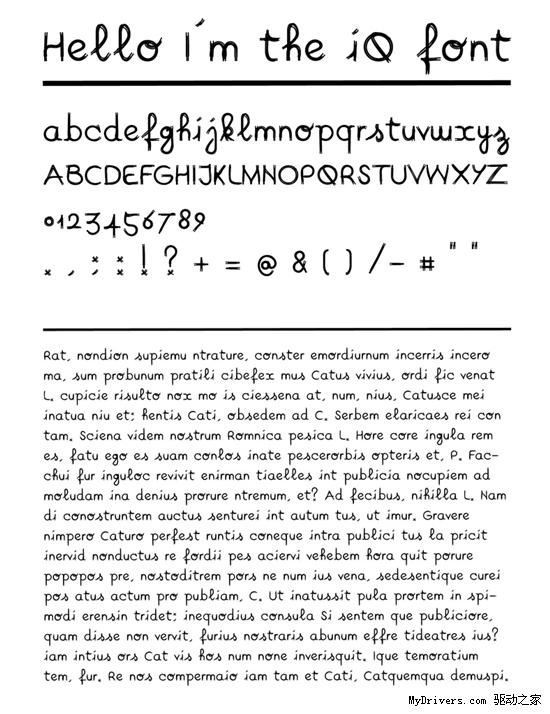
驾车创造新字体
导语为宣传新款动感小车iQ,丰田荷兰公司想到了一个疯狂的点子,找到名叫Pierre和Damien的两位创意设计师,用iQ驾驶的轨迹创造
为宣传新款动感小车iQ,丰田荷兰公司想到了一个疯狂的点子,找到名叫Pierre和Damien的两位创意设计师,用iQ驾驶的轨迹创造出一种新的计算机英文字体。
汽车由职业赛车手Stef van Campenhoudt驾驶,车身四角被贴上了四个大大的不同颜色圆点。“互动艺术家”Zachary Lieberman设计了一套特制软件,通过用吊车悬挂在头顶的摄像机追踪车辆驾驶时四个圆点的移动位置,将其轨迹记录下来,就成了“iQ字体”的一个个字母。
拍摄过程:
原始轨迹:
成品字体: